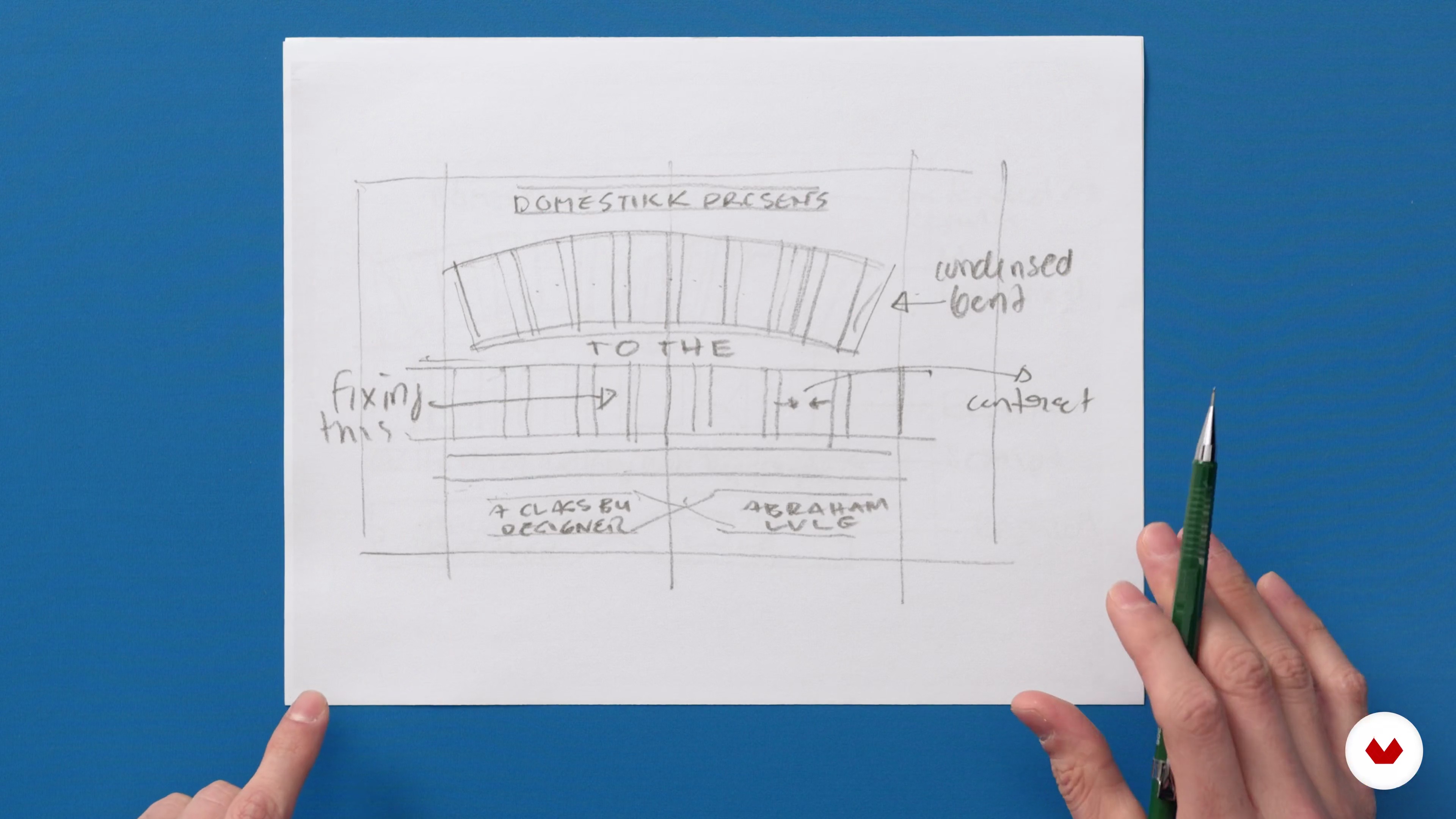
Sketching
Sobre a videoaula: Sketching
Visão geral
“Nesta lição, vou mostrar meu processo de desenho. Com um único pedaço de papel, lápis e qualquer forma de borracha, o que aprendemos no capítulo anterior está prestes a ser mostrado em uso.”
Nesta videoaula, Abraham Lule aborda o tópico: Sketching,que faz parte do curso online da Domestika: Introdução ao design com letras. Explore os conceitos e princípios da tipografia para criar designs inspiradores.
Transcrição parcial do vídeo
“Sketching Agora que aprendemos os conceitos e elementos do design, nesta lição, começaremos a esboçar. Existem muitas maneiras pelas quais os designers fazem seu trabalho em esboços. O meu é bastante simples, mas também muito difícil. Pessoalmente, preciso apenas de algumas linhas e notas para eu entender e saber o que fazer no computador. Já fiz alguns para você e vou orientá-lo através deles. A primeira coisa que faço é transmitir a mensagem; neste caso, será este curso: Domestika Presents, Atenção às cartas, ou a arte de trabalhar com tipografia, uma aula do designer, Abraham Lule. Assim...”